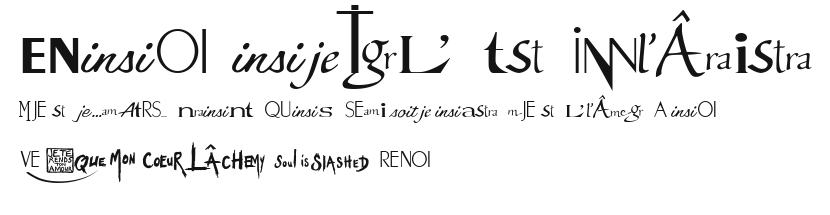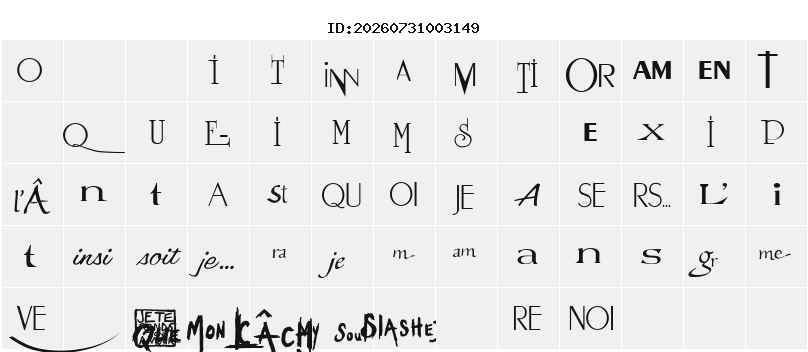
• Font Name: Logos Mylène Farmer
• Designer: Eddy Béchu (Keyan)
• Description: Cette police a été créée pour reproduire les logos de plusieurs chansons de Mylène Farmer (design de Com N'B): l'âme-stram-gram, optimistique-moi, innamoramento, l'instant X, à quoi je sers..., que mon coeur lâche, my soul is slashed, je te rends ton amour, ainsi soit je...